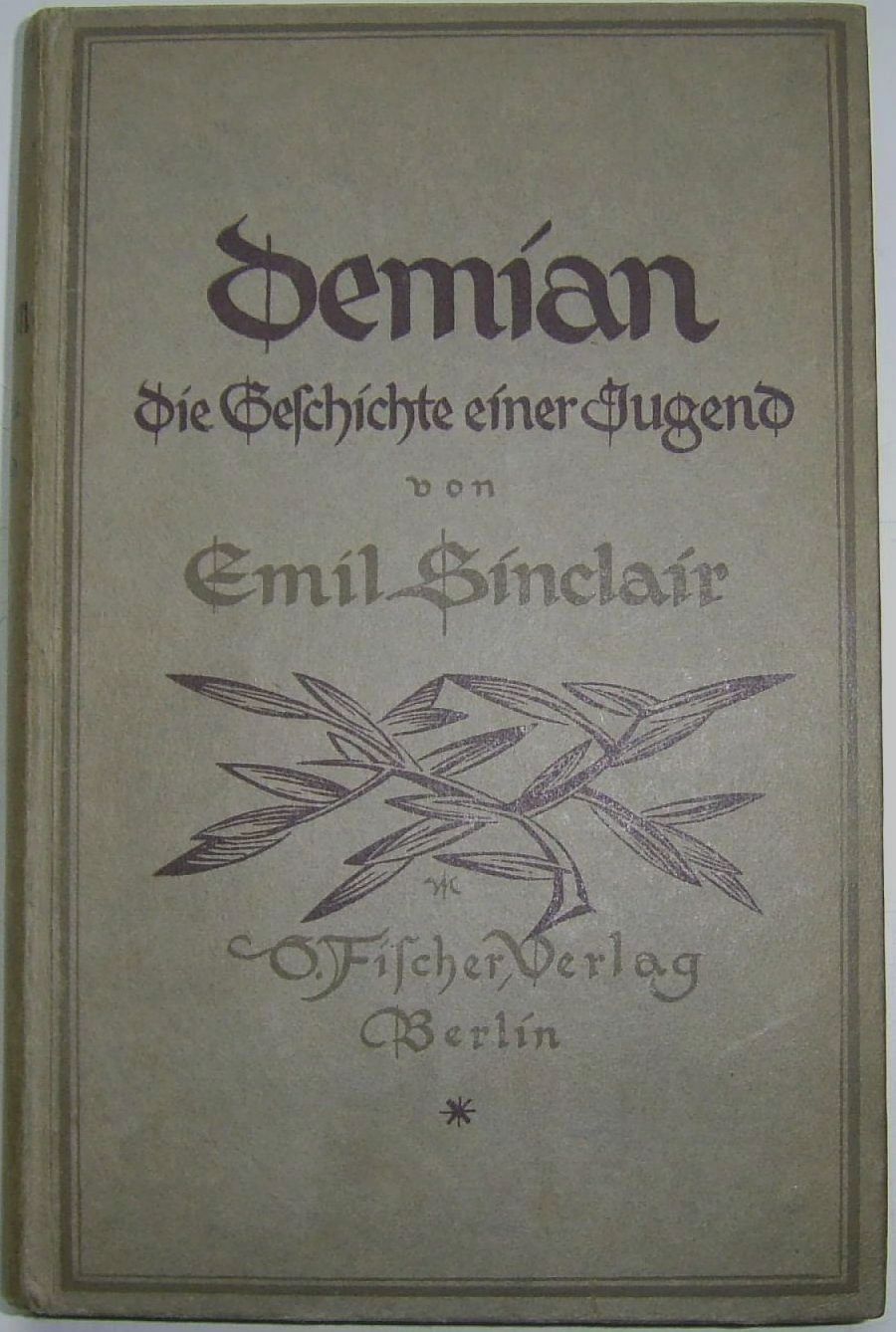
Hesses Demian – Erstausgabe
Ich bin gerade auf diesen Buchtitel gestoßen und wollte mal rumfragen, ob jemand etwas über diese Schrift weiß (Name, Gestalter, ...)
Das ›D‹ und das ›J‹ finde ich ziemlich cool ...
Okay, jetzt sehe ich es auch.